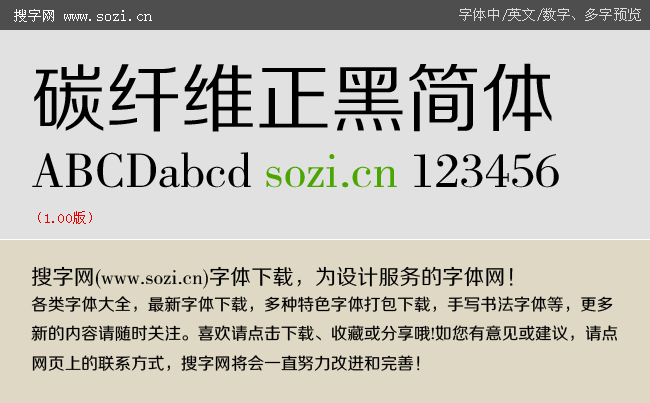
碳纖維正黑簡(jiǎn)體
本字體應(yīng)開(kāi)發(fā)者方正字體要求已下架,謝謝您的理解與支持!搜字網(wǎng)提供一碳纖維正黑簡(jiǎn)體中文藝術(shù)字體下載,正黑體取傳統(tǒng)黑體結(jié)構(gòu),筆形全部采用平行、垂直與弧度的流線(xiàn)形設(shè)計(jì),簡(jiǎn)潔易識(shí)、美觀大方,具有個(gè)性,加之鏡像對(duì)稱(chēng)的現(xiàn)代構(gòu)成形式,達(dá)到莊重與簡(jiǎn)潔有機(jī)融合、設(shè)計(jì)感與閱讀功能兼?zhèn)涞淖罱K效果。適合書(shū)籍排版,報(bào)紙排版,海報(bào)設(shè)計(jì),包裝設(shè)計(jì)等廣告設(shè)計(jì)場(chǎng)合應(yīng)用。